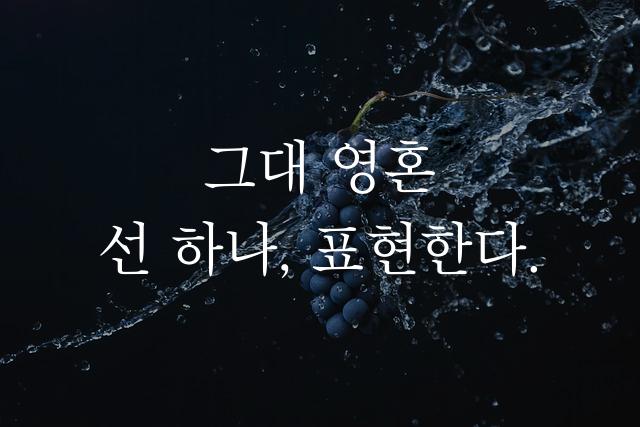
조선일보명조체는 문서 작성에 최적화된 바탕체로, 전통 명조 스타일을 현대적으로 재해석한 폰트입니다. 책과 같은 인쇄 매체에 적합하며, 한글의 아름다움을 세련되게 표현해줍니다.
조선일보명조체은(는)
바탕 스타일, 명조/전통, 복고풍 계열의 생김새를 가지고 있으며
출판 디자인, 보고서/문서, 출판물 제목 등에서 자주 활용되며, 효과적인 메시지 전달에 적합합니다.
이 폰트는 출판/미디어, 공공/정부, 금융/비즈니스 분야에 잘 어울리며,
전문적인, 고급스러운, 클래식한 느낌을 담고 있는 것이 특징입니다.
이 폰트와 유사한 폰트로는 나눔명조, 바탕체, 굴림체, 돋움체 등이 있어요. 함께 비교해 보시면 좋습니다!